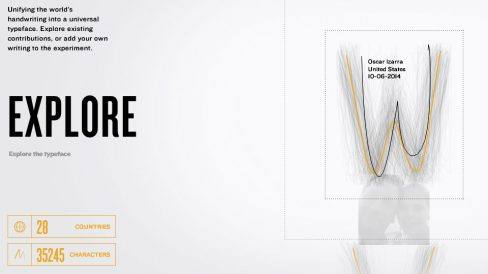
Bic quer criar uma tipografia universal baseada em letra de mão
Marca se envolve com digital ao propor uma fonte que seja bem parecida com a escrita feita à mão
O desenho de cada uma das letras do alfabeto é feito de jeitos diferentes dependendo de onde você foi alfabetizado, o tipo de profissão que seguiu, gênero e até se é canhoto ou destro.
Pensando em trazer essas letras ‘analógicas’ para o ambiente digital, a Bic, em parceria com a DDB Düsseldorf e a MediaMonks, decidiu fazer um curioso experimento: querem criar uma tipografia universal, com base na grafia das letras de pessoas do mundo todo.
Para isso, a marca está pedindo que os usuários enviem exemplos de sua grafia em letra de mão para o site theuniversaltypeface.com, onde as amostras serão analisadas e utilizadas na confecção da nova fonte universal, que deverá ser lançada em agosto.
No site, também é possível ver como é o estilo de escrita mais comum em diferentes países, para diferentes profissões, gêneros, e qual a diferença de grafia entre destros e canhotos, evidenciando que a letra de mão é algo único e bastante pessoal no mundo todo.
As amostras enviadas pelos usuários serão analisadas e utilizadas na confecção da nova fonte universal, que deverá ser lançada em agosto.
“Existem poucas coisas que são mais pessoais do que a sua própria letra. Então pensamos que seria um experimento legal se pudéssemos ver como trazer esse estilo pessoal para algo mais global”, explica Dennis May, da DDB Düsseldorf, em entrevista ao Digiday
É engraçado, contudo, que o experimento não use –pasme!- uma Bic para isso. No site, os colaboradores podem desenhar a letra usando o mouse ou através de dispositivos com touchscreen, como smartphones e tablets. Ainda assim, o resultado pode sair bem diferente daquele que seria obtido com um lápis ou caneta.
Até o momento, mais de 35 mil pessoas de 28 países já enviaram suas amostras de letra de mão para o site.
Acho legal que uma marca que é fundada em um conceito analógico, como a escrita manual, possa mostrar que é possível mesclar antigo com novo e trazer dados interessantes desse tipo de experimento.
E pensar que a Bic de tubinho amarelo já é quase um produto retrô, hein?